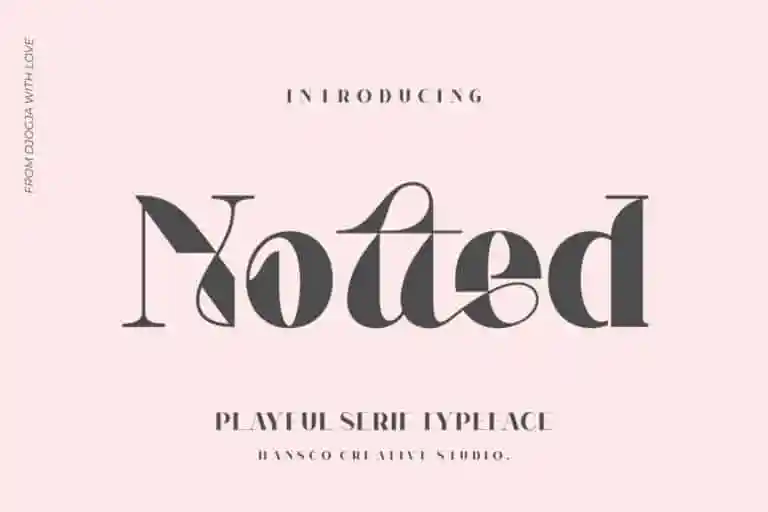
Notted Display Font – Download Grátis
A Notted Display Font é uma fonte criada por HansCo inspirada nos posters vintage do setor fashion dos anos 70. Este design apresenta um toque moderno, repleto de estilos e personalidade. É perfeitamente adequado para uso em marcas, embalagens, logotipos, casamentos, revistas, jornais, cartões de agradecimento e muito mais. Se você está procurando uma fonte elegante para dar um toque único aos seus projetos, esta é certamente a escolha perfeita. Adquira agora e deixe que sua identidade gráfica seja o destaque em qualquer projeto!